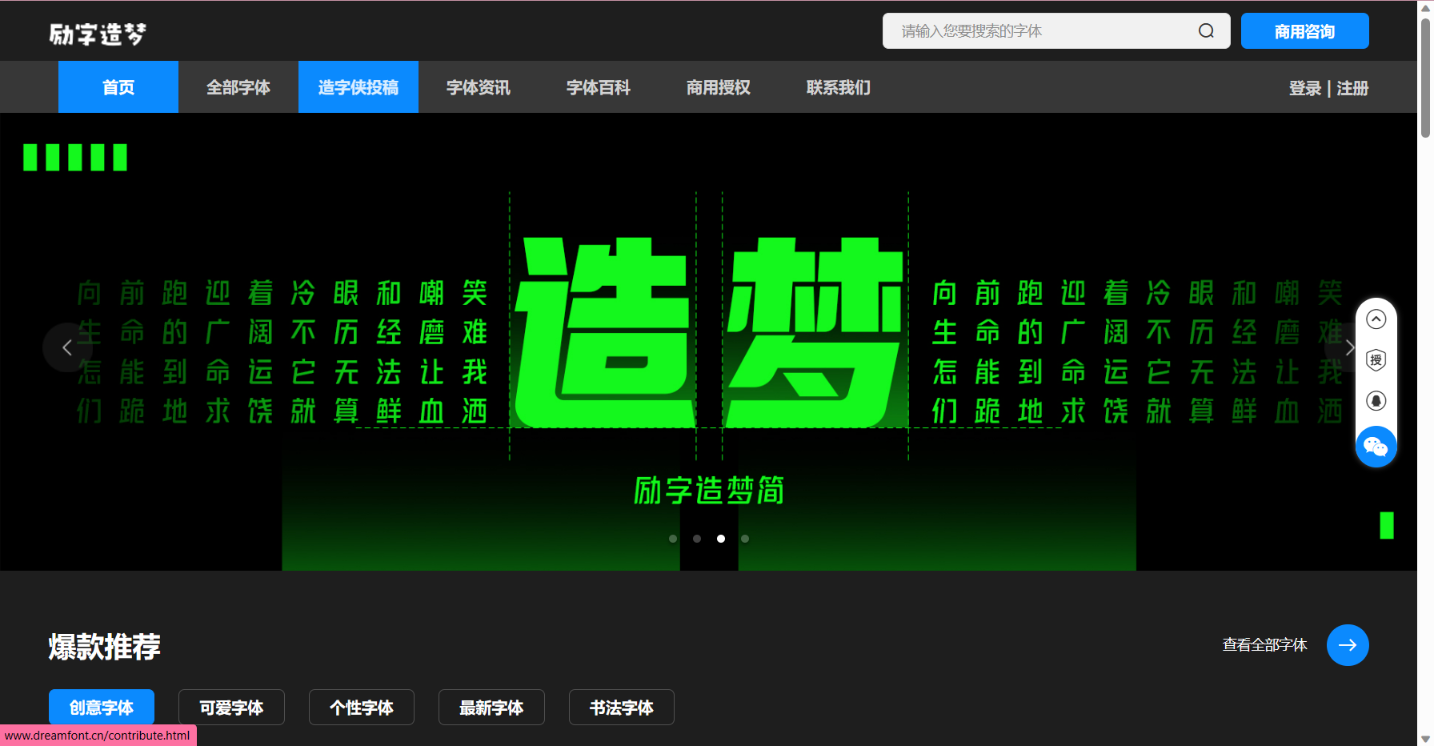
励志青春类的字体是年轻永恒的主题,无论是广告,平面,视频还是和品包装,针对年轻人的产品总是拥有无限的流量。
励字造梦字库是一个励志青春的创意字库品牌,旗下包括造字侠、励字字库,玩转创意,挥发想象,将设计师们的原创灵感与理念融入到字体中,打造字型丰富、个性十足、灵动百变的创意字库。
同时作为一个持续产出优质字体与设计风尚的新生态开放字库,打造汉字「新」趋势,开放字体合作渠道,让更多热爱汉字设计的人,实现造字梦想。